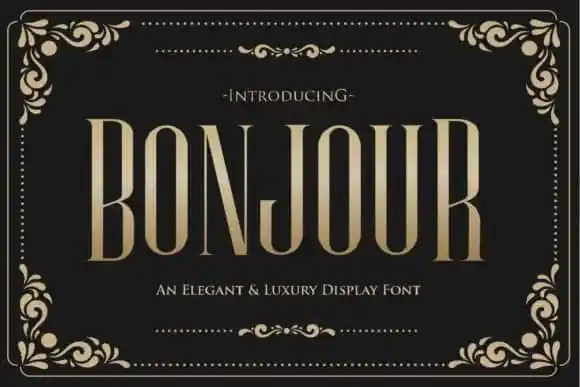
Bonjour Display Font – Fonte Grátis
Bonjour Display Font
Bonjour Display Font é uma fonte serif que foi projetada cuidadosamente por técnicas artesanais. Esta tipografia foi criada pela Gilar Studio e compartilhada com o mundo. É uma nova fonte serif elegante ideal para aumentar a sofisticação em seus projetos de marca, logotipos, monogramas para casamentos e convites, headlines para blogs e muito mais. Através das várias pré-vizualizações, podemos ver como ela potencialmente revigora e adiciona um toque luxuoso a qualquer projeto. Se você está procurando por uma fonte que possa trazer ao seu design uma sensação de elegância sem comprometer a legibilidade, Bonjour Display Font é definitivamente algo para olhar mais de perto.